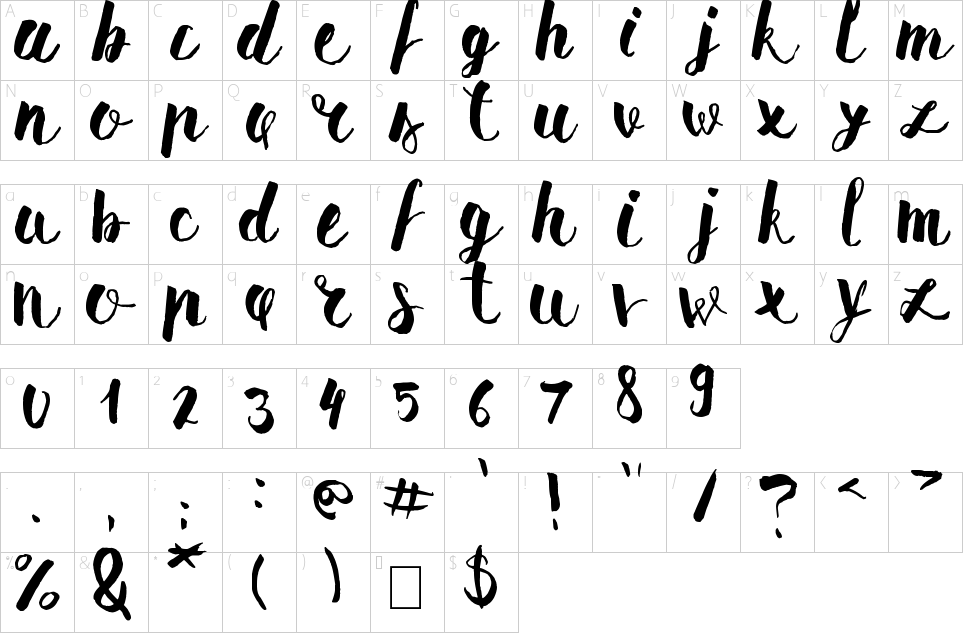
A fonte Pomah Type é um recurso grátis para designers e criativos de todo o mundo, desenvolvida pelo designer Leosupply.co. Esta fonte apresenta um estilo limpo e elegante, ideal para uma variedade de usos, desde criação de websites até editoração de revistas impressas. Foi projetada para oferecer uma experiência visual agradável e eficaz, sem comprometer a estética. Com uma versão gratuita para Windows e Mac, qualquer criador pode explorar seus recursos únicos. Em um mundo cada vez mais competitivo e visual, ter uma fonte de qualidade como a Pomah Type pode fazer toda a diferença no seu trabalho. Download esta fonte de graça e experimente suas opções incríveis.